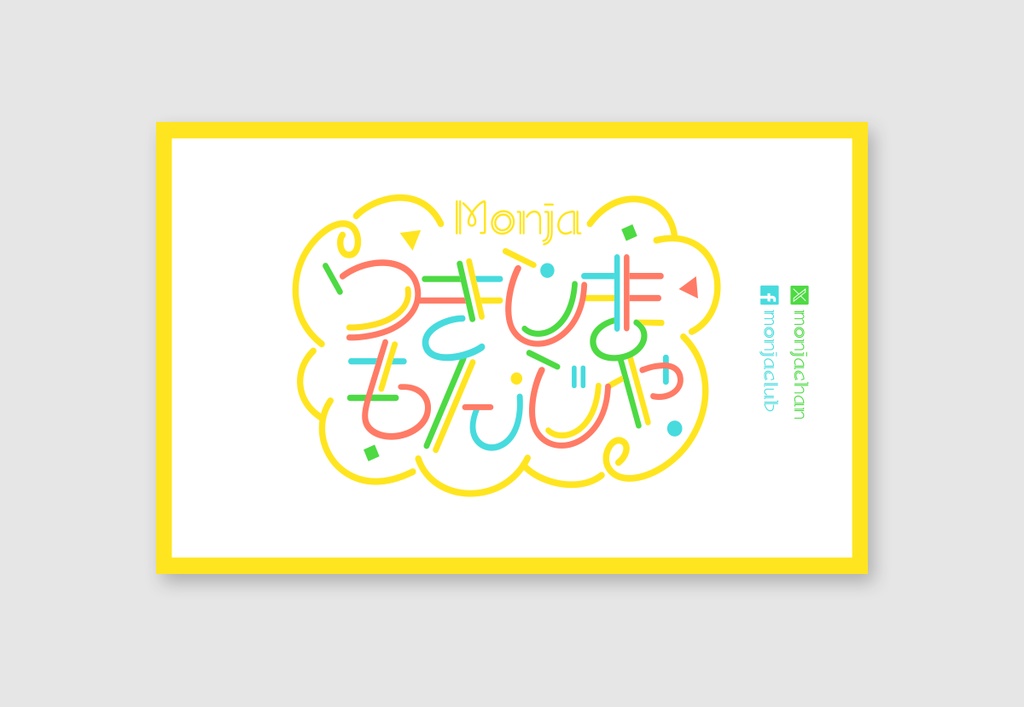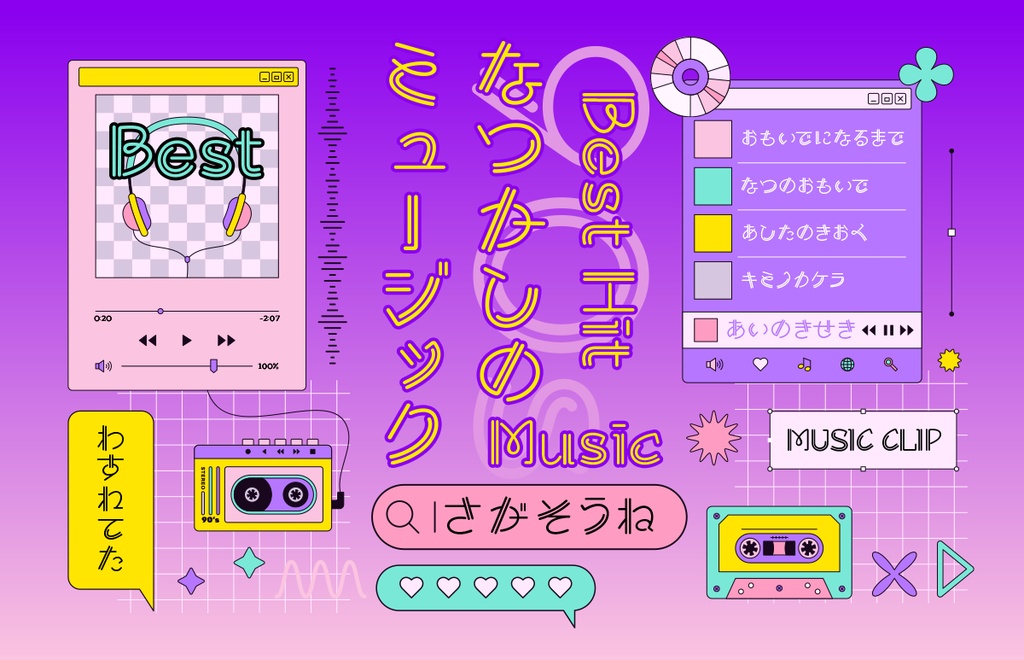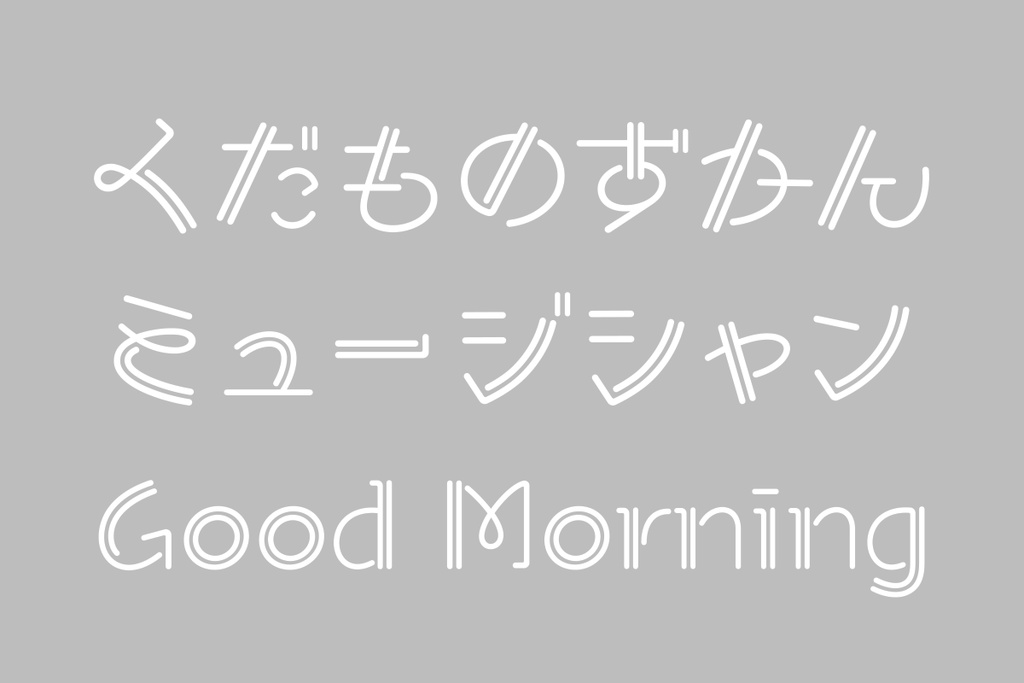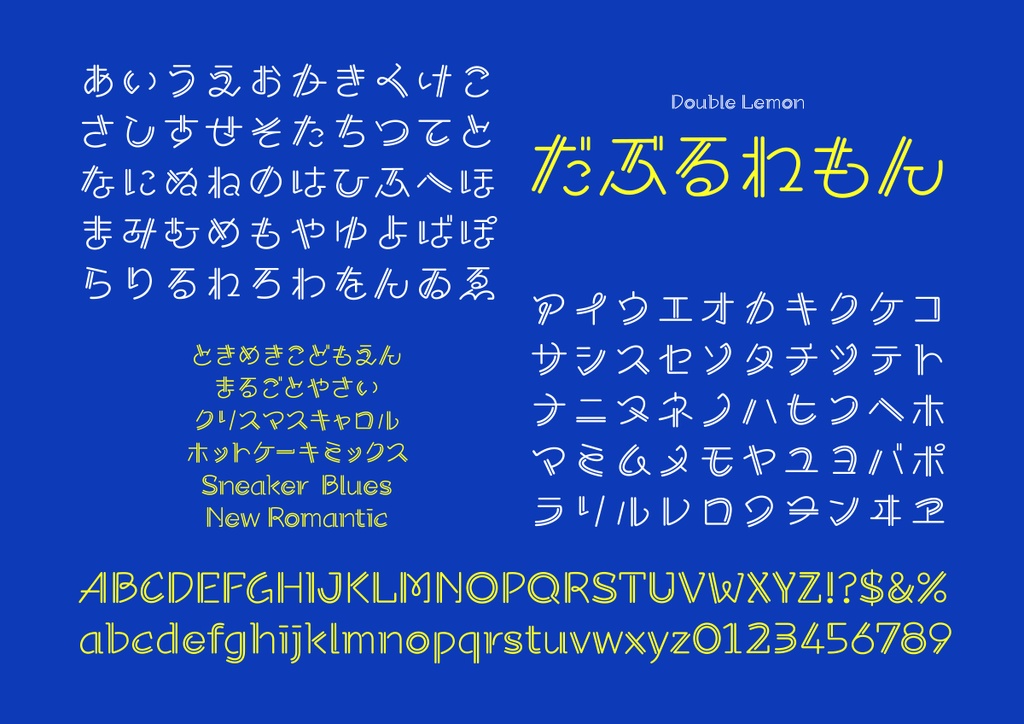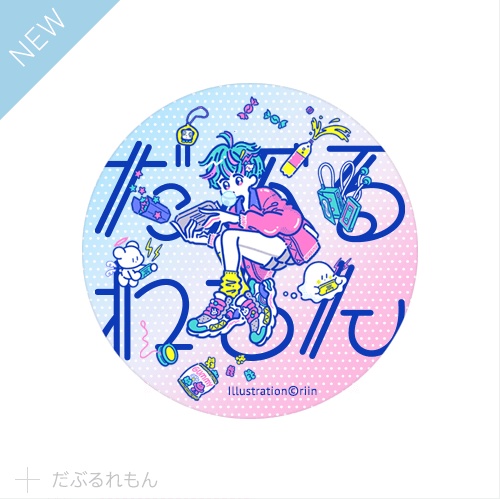
だぶるれもん フォント
ポップでどこか懐かしい丸ゴシック体フォント「だぶるれもん」。2本線が印象的なデザインは、使うだけでハッピー気分。 ■動作環境 Mac:システム/OS X対応(10.x)〜最新のOS X Windows:OS/日本語版Windows2000、XP、VISTA、Windows7〜12以降 フォント形式:OpenTypeフォント 1商品(1ライセンス)につき1ユーザー1PCのみがご利用いただけます。複数人で使用する場合は人数分をご購入ください。 ■収録文字について 収録文字数439字。※収録文字はアルファベット、ひらがな、カタカナ、約物の一部。 ■安心して使えるロイヤリティフリーの書体 あらゆる商用・デザイン用途(印刷物・ゲーム・アプリ・映像・動画・ロゴ・同人作品)に使用できる、商用申請の必要のないロイヤリティフリーの書体になります。文字の加工・変形も可能です。ご安心ください。 ■OpenType機能 詰め組み機能 ペアカーニング(仮名・プロポーショナル欧文) 字形切り替え機能(1つの文字で異なる字形を用意しています)